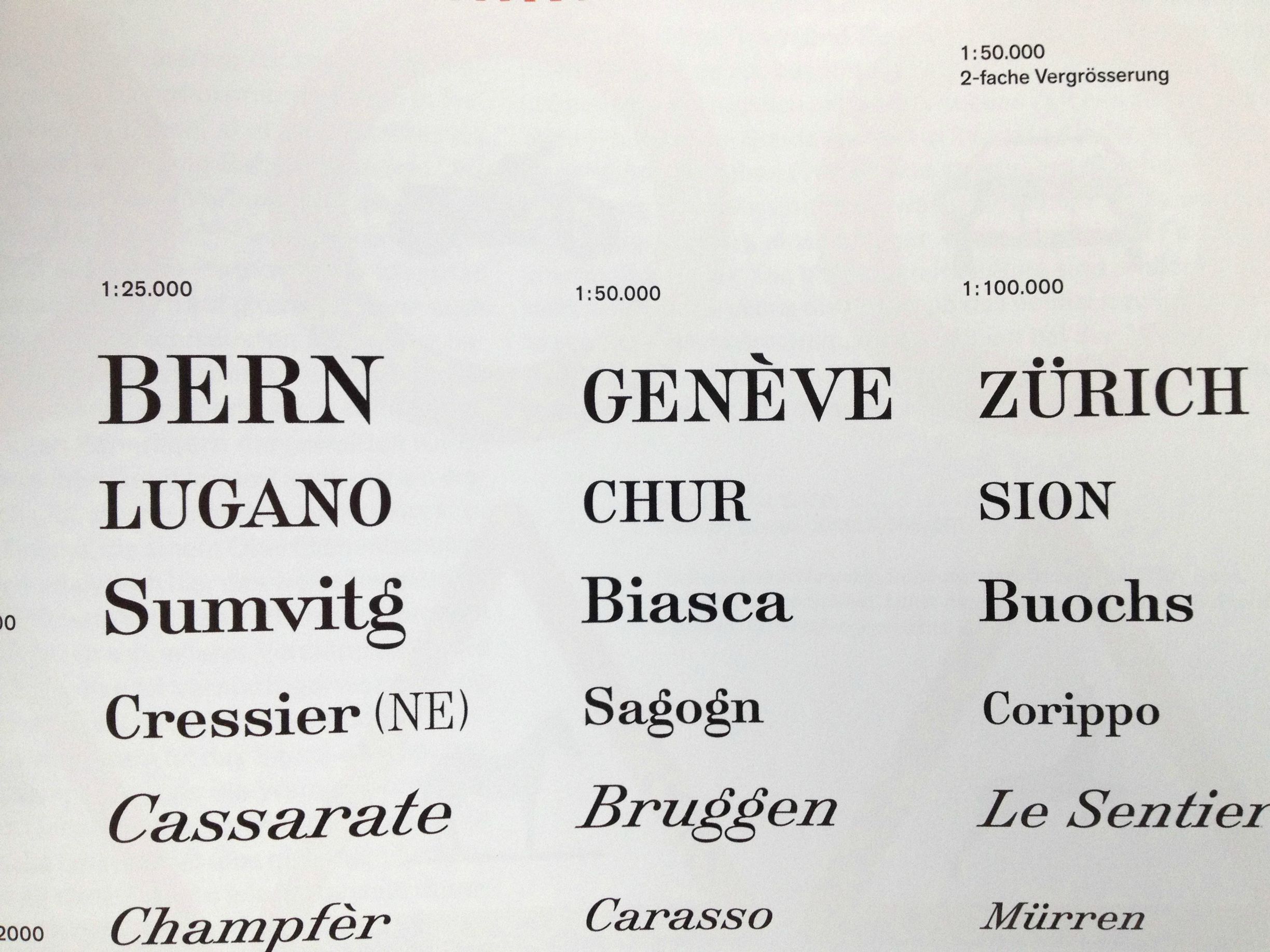
Schweizer Kartografieschriften
ich bin auf der Suche nach einer digitalen Version klassischer Kartografieschriften (in meinem Fall von Schweizer Landkarten, aber sicherlich wurden ähnliche Schriften auch in anderen Ländern verwendet).
Die Century Schoolbook kommt recht nahe dran, aber es gibt eben doch einige Details, die sehr eigen sind: Die sehr runden Ansätze der Serifen, das geschwungene G, das sehr auffällige senkrechte Fähnchen beim g, die stark geneigte Kursive (das Foto ist etwas ) etc.
forums-kollege sebastian nagel hat eine „karten“-schrift entworfen. schau dir die mal an. sieht zwar stark anders aus als in deinem beispiel (das vorbild stammt auch aus einem anderen jahrhundert als deines), hat aber ihren reiz!
Ja, ähnliche (mit diesem markanten g) gibt es.
Siehe vor allem die Römisch in unserer entsprechenden Liste: http://www.typografie.info/3/page/Schriften/listen.html/_/kartografie-fonts-für-landkarten-und-stadtpläne-r15